En el vasto universo de la informática, existen pequeños detalles que, aunque a menudo pasados por alto, definieron la experiencia de millones de usuarios. Uno de estos héroes anónimos es la tipografía del Bloc de Notas, esa herramienta simple pero omnipresente en todas las versiones de Windows. Durante años, una fuente en particular reinó en esa ventana blanca: Fixedsys. Este artículo es un viaje al corazón de la tipografía digital, explorando no solo la fuente por defecto de Notepad, sino también el ecosistema tipográfico del legendario Windows XP, un sistema operativo que marcó a toda una generación.
El Origen y Reinado de Fixedsys
Para entender la importancia de Fixedsys, debemos retroceder en el tiempo. Su nombre, que significa "sistema fijo" (del inglés fixed system), ya nos da una pista crucial sobre su naturaleza: es una familia de fuentes monoespaciadas de tipo rasterizado. Esto significa que cada carácter, sin importar si es una 'i' o una 'W', ocupa exactamente el mismo ancho horizontal. Esta característica es fundamental para tareas como la programación, donde la alineación vertical del código es esencial para la legibilidad.
Fixedsys es, de hecho, la fuente más antigua de Microsoft Windows. Fue la tipografía del sistema en Windows 1.0 y 2.0, donde se le conocía simplemente como "System". Con la llegada de Windows 3.x, el sistema adoptó una nueva fuente sans-serif proporcional, pero Fixedsys no desapareció. Encontró su hogar definitivo como la fuente predeterminada en el Bloc de Notas, un rol que mantuvo firmemente a través de Windows 95, 98 y Windows Me.
Diseñada originalmente por Bitstream Inc. en 1984, con una versión de alta resolución creada por Microsoft en 1987, Fixedsys tiene un aspecto particular. Aunque es una fuente sans-serif (sin remates), su diseño pixelado evoca la apariencia de las fuentes de modo texto de hardware de los primeros PCs compatibles con IBM. A diferencia de otras fuentes monoespaciadas como Courier, en Fixedsys los caracteres en negrita son ligeramente más anchos que sus contrapartes normales, un detalle técnico que la distingue.
¿Por qué era tan apreciada?
Su popularidad, especialmente en la comunidad de desarrolladores, no fue casualidad. Su estilo limpio, su excelente legibilidad en tamaños pequeños y su clara diferenciación entre caracteres similares (como el '0' y la 'O', o la 'l' y el '1') la convirtieron en una herramienta de trabajo fiable. Era predecible, funcional y no tenía distracciones. Su encanto era tal que inspiró la creación de una fuente de imitación moderna, Fixedsys Excelsior, que tomó la base del diseño original y la expandió para incluir un vasto número de rangos de escritura Unicode, llevándola al siglo XXI.
La Transición: De Fixedsys a Lucida Console
El cambio de milenio trajo consigo nuevos sistemas operativos y una evolución en el diseño de interfaces. Con la llegada de Windows 2000 y, más notablemente, Windows XP, Microsoft decidió modernizar la apariencia de sus aplicaciones. El Bloc de Notas no fue una excepción. Fixedsys fue finalmente reemplazada por Lucida Console como la fuente por defecto.
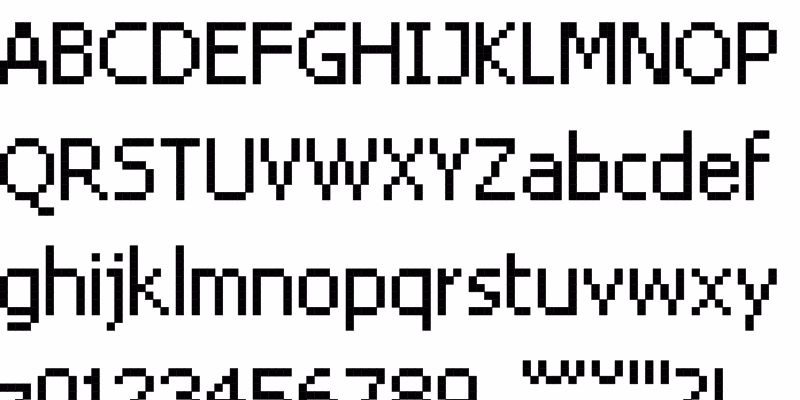
Este cambio no fue meramente estético; representó un salto tecnológico significativo. Mientras que Fixedsys es una fuente rasterizada (o de mapa de bits), Lucida Console es una fuente TrueType, es decir, vectorial. La diferencia es fundamental: las fuentes rasterizadas están compuestas por una cuadrícula fija de píxeles y no escalan bien. Si intentas aumentar su tamaño, los bordes se vuelven dentados y pierden definición. En cambio, las fuentes vectoriales se definen mediante ecuaciones matemáticas, lo que les permite escalar a cualquier tamaño sin perder nitidez.
Tabla Comparativa: Fixedsys vs. Lucida Console
| Característica | Fixedsys | Lucida Console |
|---|---|---|
| Tipo de Fuente | Rasterizada (Mapa de bits) | Vectorial (TrueType) |
| Escalabilidad | Pobre, solo se ve bien en tamaños específicos. | Excelente, nítida a cualquier tamaño. |
| Soporte de Caracteres | Limitado a páginas de códigos específicas. | Amplio soporte Unicode. |
| Apariencia | Pixelada, retro, nítida en su tamaño nativo. | Suave, moderna y redondeada. |
| Época Predeterminada | Windows 1.0 - Windows Me | Windows 2000 / XP en adelante |
La Tipografía en el Ecosistema de Windows XP
El cambio en Notepad fue solo una parte de una estrategia tipográfica mucho más amplia en Windows XP. Para mejorar la jerarquía visual y el interés, y para alinearse mejor con la marca Microsoft, XP introdujo un conjunto de tipografías cuidadosamente seleccionadas para diferentes partes de la interfaz de usuario.